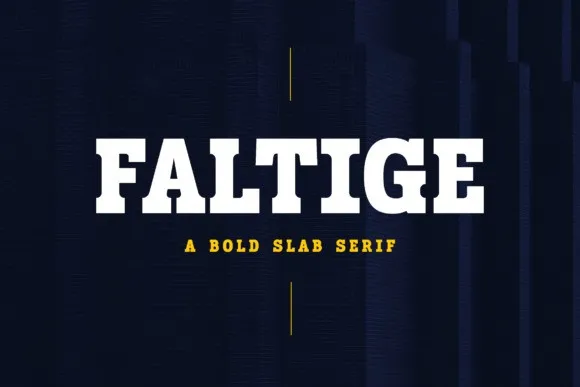
A Faltige Font é uma slab serif que se inspira nas tipografias desportivas e está repleta de vitalidade e energia, com um toque masculino e atemporal. Inspirada nos símbolos esportivos, essa fonte exala a essência do esporte em sua forma mais pura e poderosa. Seu design é perfeito para uma variedade de aplicações, desde criação de marca até decoração de casas, passando por editoriais, adesivos de badge ou até mesmo materiais educativos. Seja para um site de blog fashionista, logotipos sofisticados ou até mesmo títulos em livros e capas de revistas, a Faltige Font oferece uma solução moderna que se alinha perfeitamente com o design moderno e vibrante atemporal que deseja expressar.